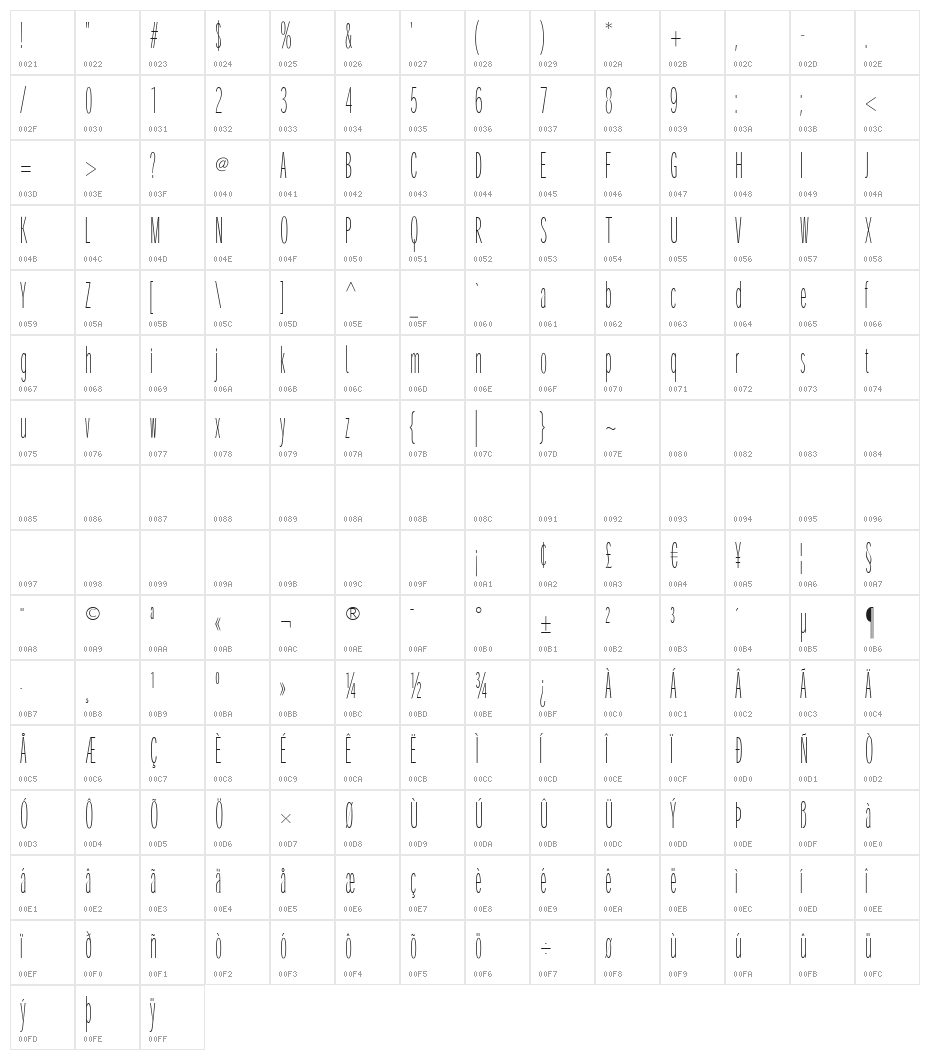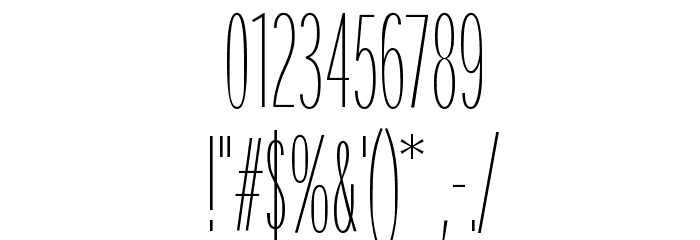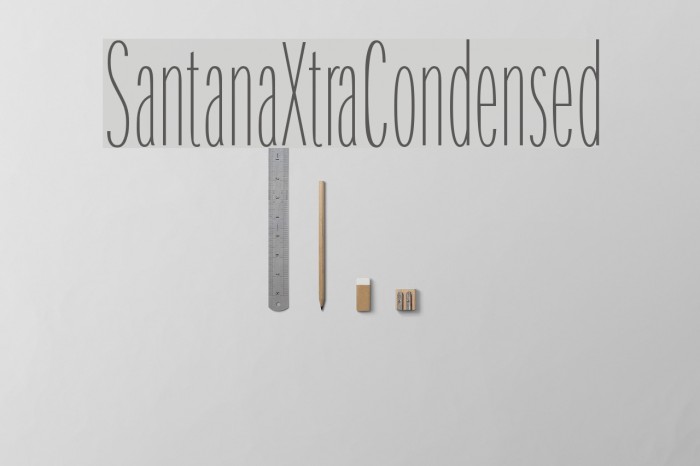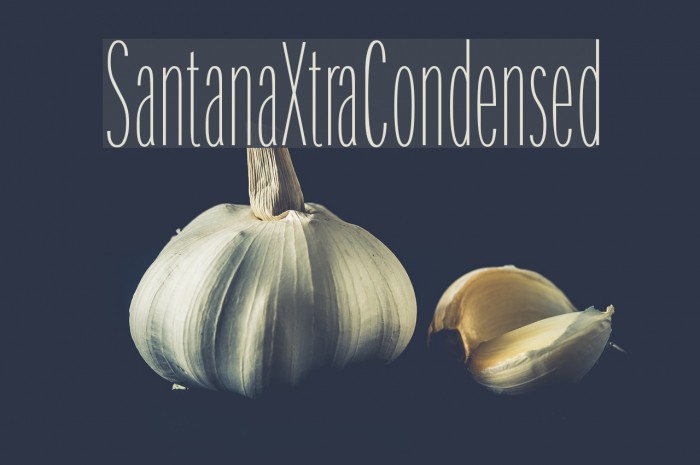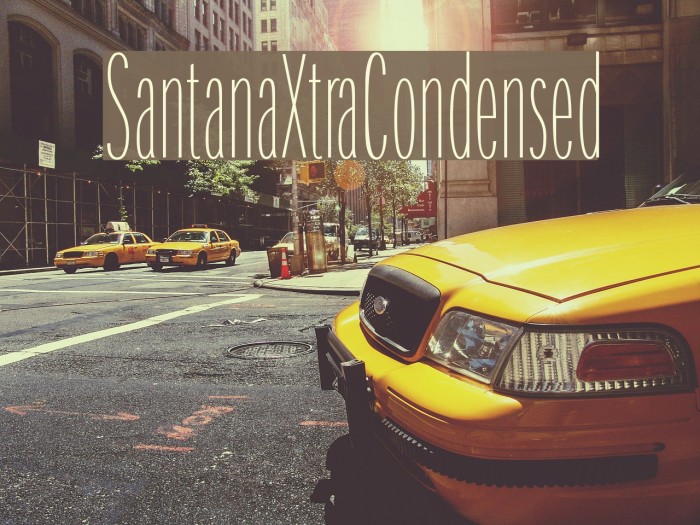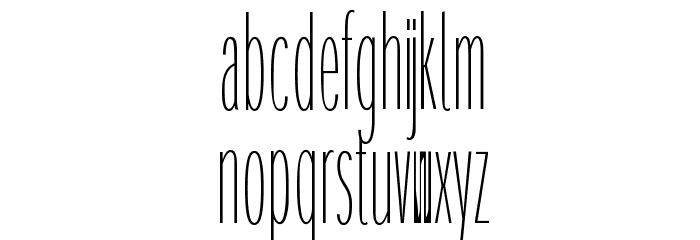
SantanaXtraCondensed Font
✎ Sans Serif
| الفئات | Sans Serif |
| العرض | Condensed |
| مشاريع مقترحة | Ideal for fashion magazines, modern branding, luxury product packaging, and minimalist posters. |